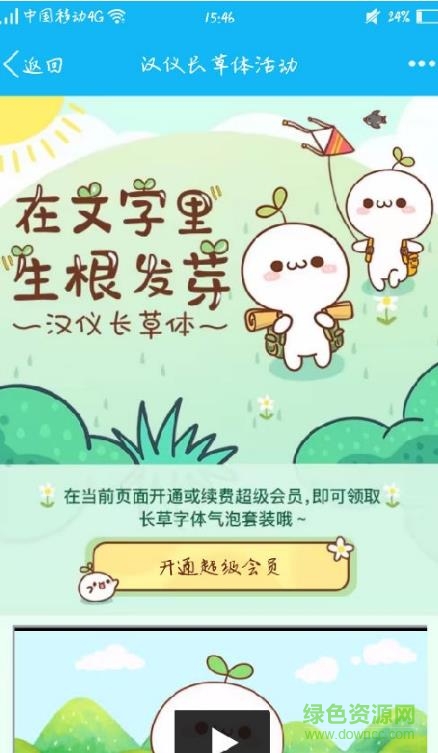
漢儀長(zhǎng)草體安裝包是一款在qq社交軟件中也能使的字體文件,讓你不僅能夠?qū)崿F(xiàn)藝術(shù)創(chuàng)作,藝術(shù)字生成,同時(shí)還能夠讓你的小伙伴領(lǐng)略到此款字體的獨(dú)特之處,為你的各類作品實(shí)現(xiàn)了畫(huà)龍點(diǎn)睛的效果!綠色資源網(wǎng)提供漢儀長(zhǎng)草體起泡鏈接下載!
可愛(ài)的漢儀長(zhǎng)草體的字在藝藝術(shù)字生成以及工業(yè)創(chuàng)作當(dāng)中受到了眾多用戶的喜愛(ài),從而備受青睞,是我所最喜愛(ài)的一款字體!